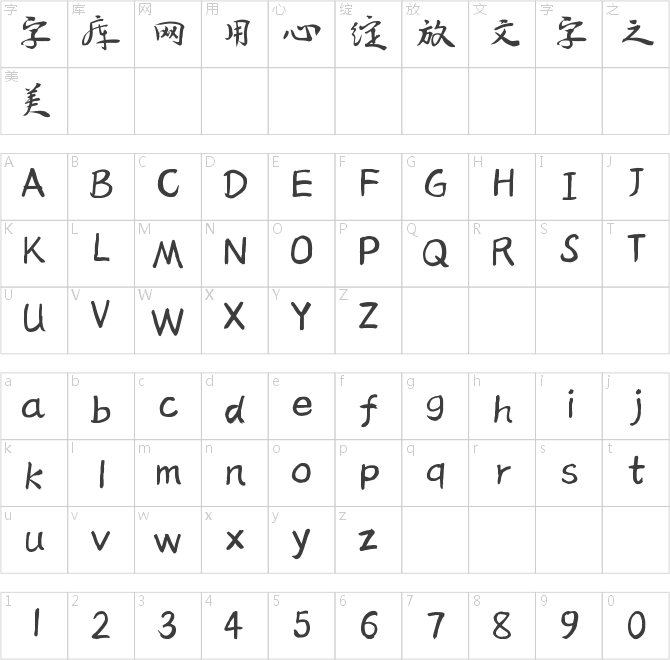
倉(cāng)耳萬(wàn)東行書(shū)
倉(cāng)耳萬(wàn)東行書(shū)字體字庫(kù)是一款讓人賞心悅目、百看不厭的中文字體,適合各類廣告和產(chǎn)品包裝設(shè)計(jì)應(yīng)用,字體大小9.51MB,格式為ttf字體,上傳用戶是黃肖,作者/版權(quán)方為倉(cāng)耳字庫(kù)